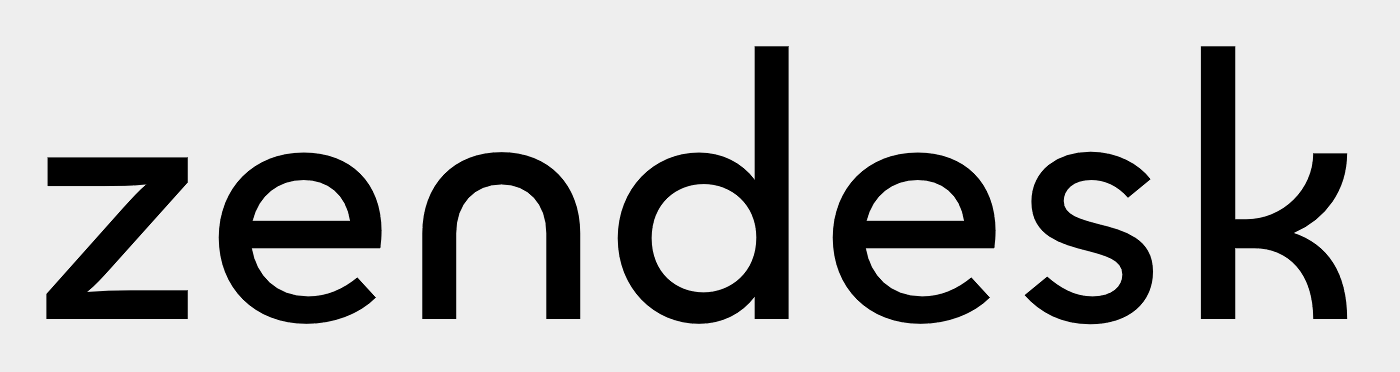
Welche Schrift könnte das sein? (zendesk)
vor 7 Stunden schrieb RobertMichael:
Auf der Website verwenden sie die Sharp Sans Nr.1 Semibold, evtl. passt die ja mit angepasstem u? Das e wurde sicher auch etwas offener beschnitten.
Gutes ist da rar gesät.
Am ehesten könnte diese passen (rundes u):
Ansonsten schau mal, ob Dir von diesen eine weiterhilft: